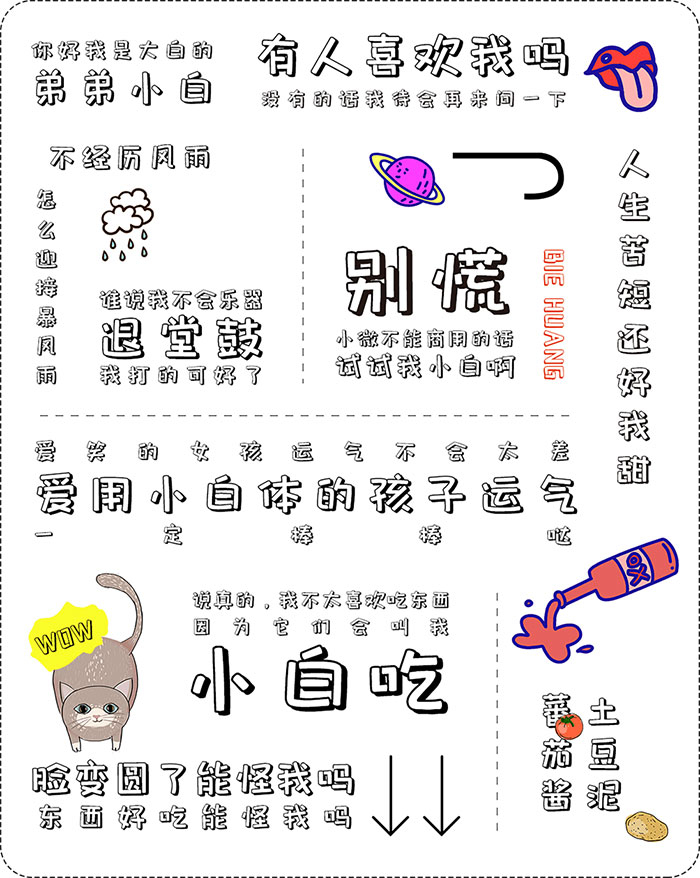
包圖小白體,原名為小白,是字體視界團隊2018年創作的一款字體,推出半年來一直廣受設計師喜愛。現由包圖網與字體視界合作,正式更名為:包圖小白體,字體版權歸包圖所有,並將字體作公益開源,向全社會開放下載並可免費商用(包括個人及企業商業用途)。
包圖小白體採用GB2312編碼,共收容7707個字符,包含6763個簡體漢字、110個大寫字母、139個小寫字母、102個數字、95個標點符號、其他特殊類符號288個、其他字母210個(包含日文平假名片假名)。
包圖小白體, 定義為一款簡單可愛的創意字體。在字形筆畫上去除了折筆的弧形,換之以平直的筆畫,豎彎鉤轉為豎折,同時弱化了鉤筆畫,省去了許多筆畫末尾的小尾巴,顯得更加直白可愛。粗短的筆畫,像柯基的小短腿,相比細長的字體能給人更多的輕鬆感。整體形態採用了鏤空的製作技巧,增強了字體的立體感,適合用於品牌標誌、海報、包裝、影視綜藝、遊戲、漫畫等場景。